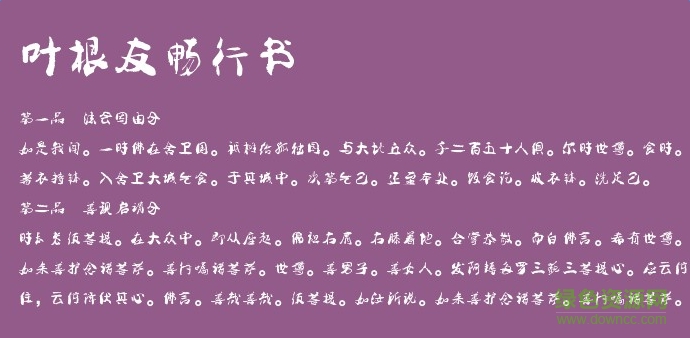
葉根友暢行書字體是一款古典優(yōu)雅風(fēng)格字體軟件,暢行書體完美闡釋了行書特點(diǎn),筆畫游走看似無章法,卻別有一番韻味,創(chuàng)意十足,非常受書法家的熱愛與追捧,還有更多好看字體歡迎來綠色資源網(wǎng)下載體驗(yàn)!
葉根友暢行書是一款2015年最新創(chuàng)作的行書字體,這款字體是葉根友行書繁的簡體風(fēng)格版本,從2008年到2015年,歷時(shí)七年的變化和書法風(fēng)格路線的創(chuàng)新,葉根友的書風(fēng)也引起了一定的變化,在字面上,書寫的更加流暢和筆勢上筆走龍蛇之輕車駕馭,在標(biāo)題應(yīng)用、廣告標(biāo)語等不錯(cuò)的應(yīng)用選擇。
該字體筆畫隨意自然,介于楷書與草書風(fēng)格之間,看似放蕩不羈,整體卻很整齊,非常有韻味,適用于標(biāo)題文章設(shè)計(jì)方面,值得使用收藏!